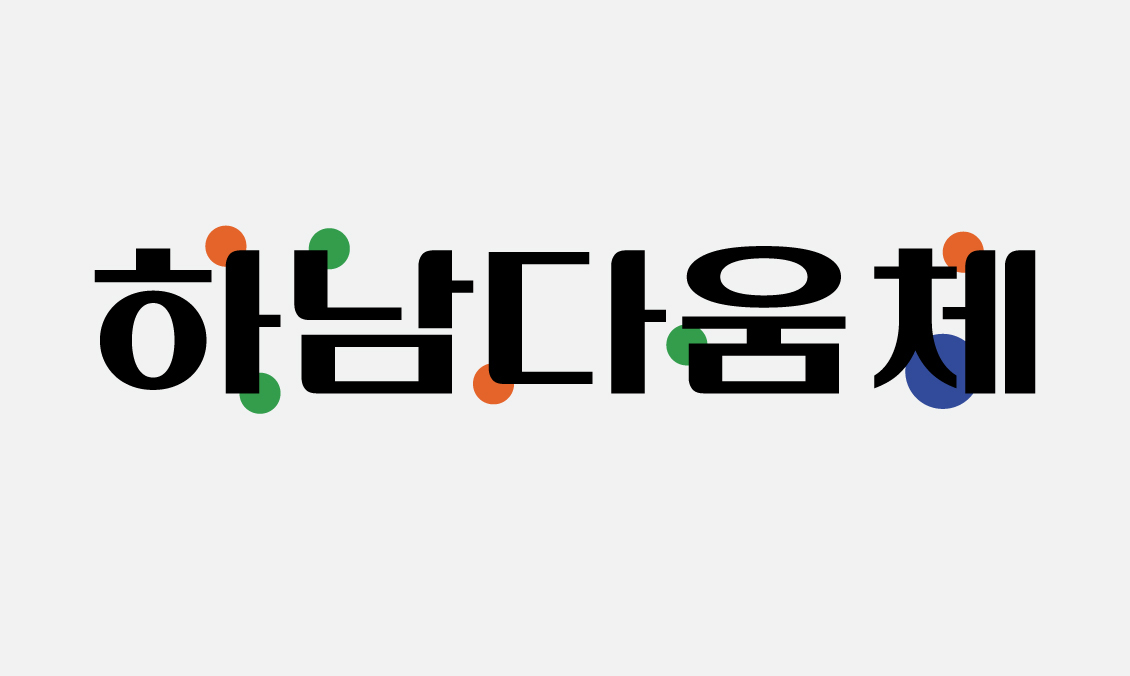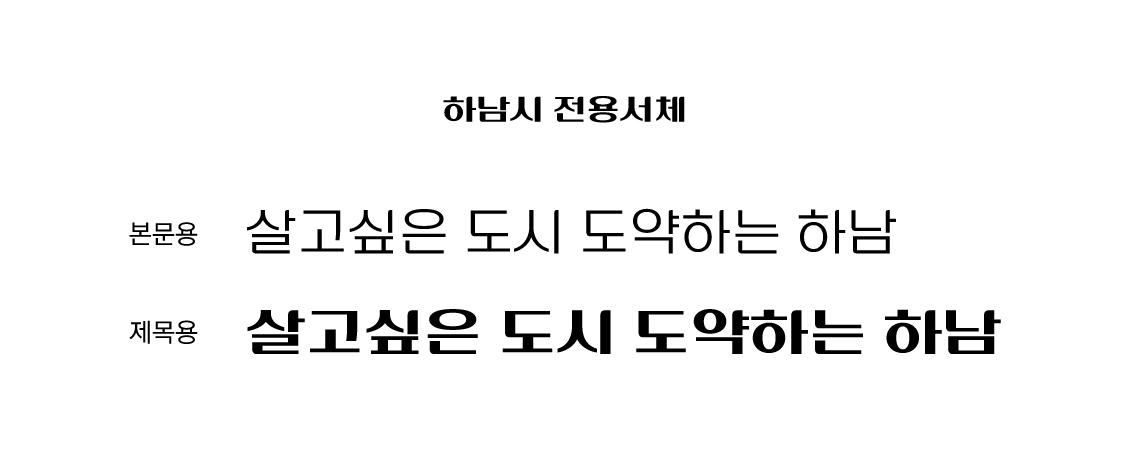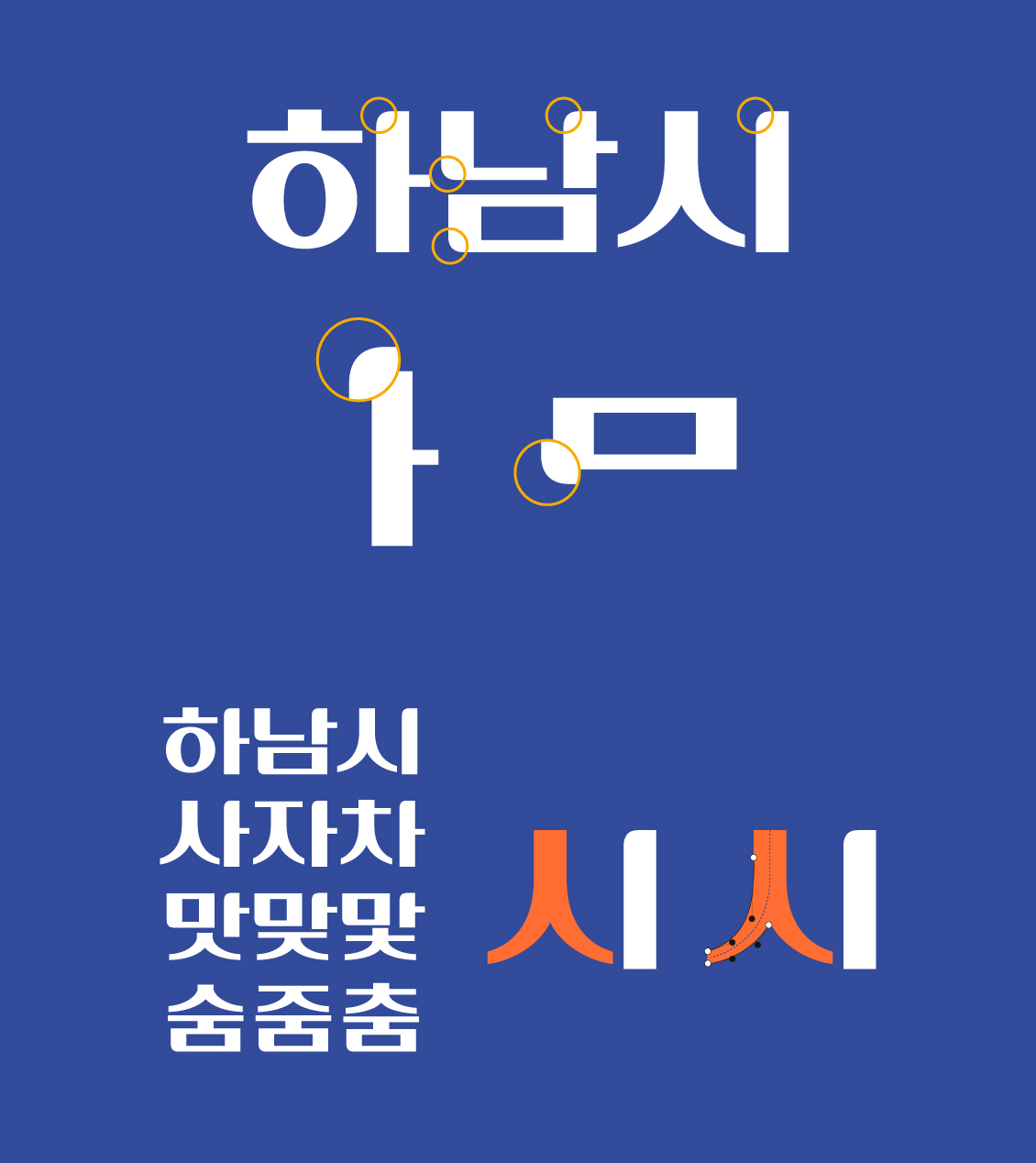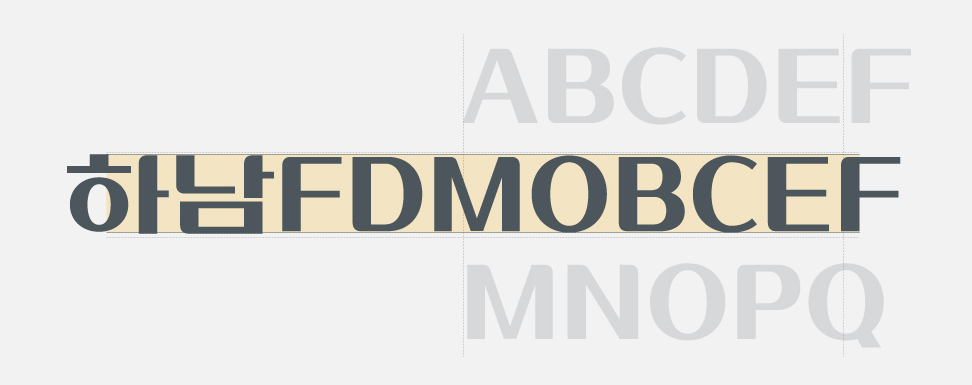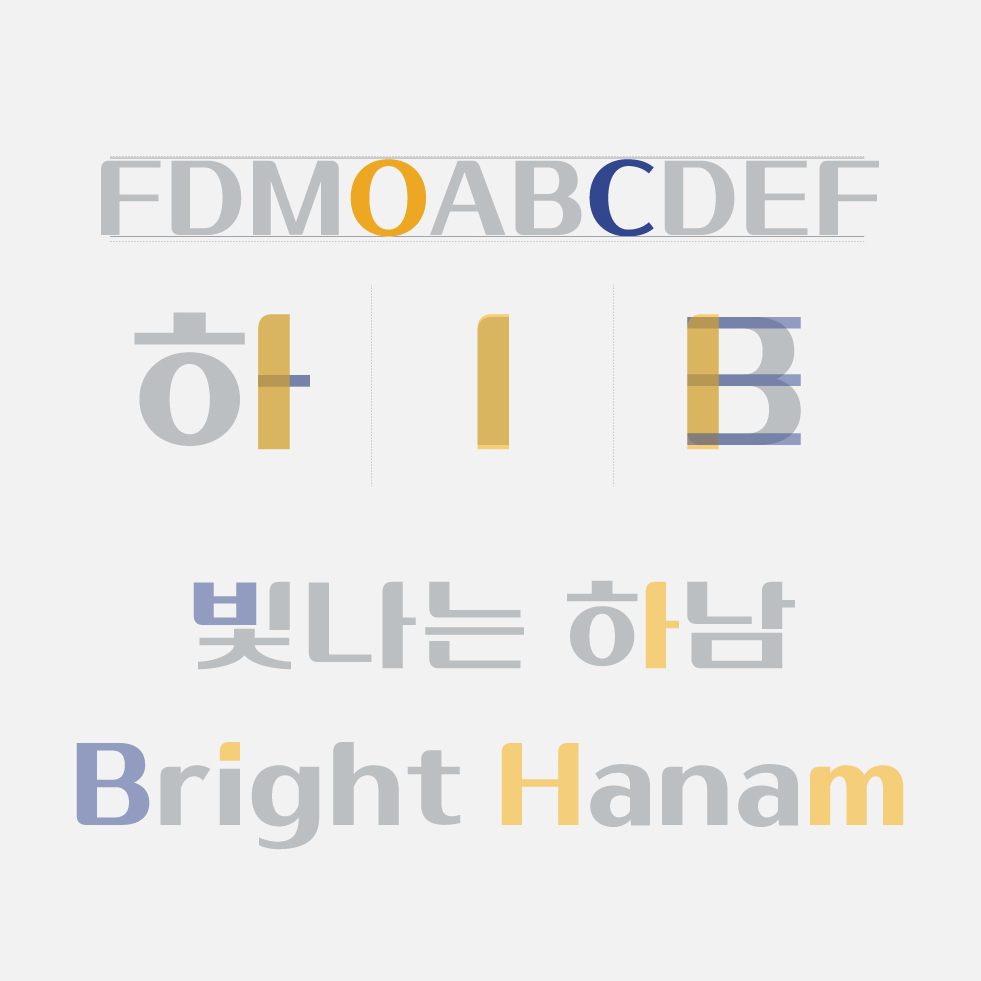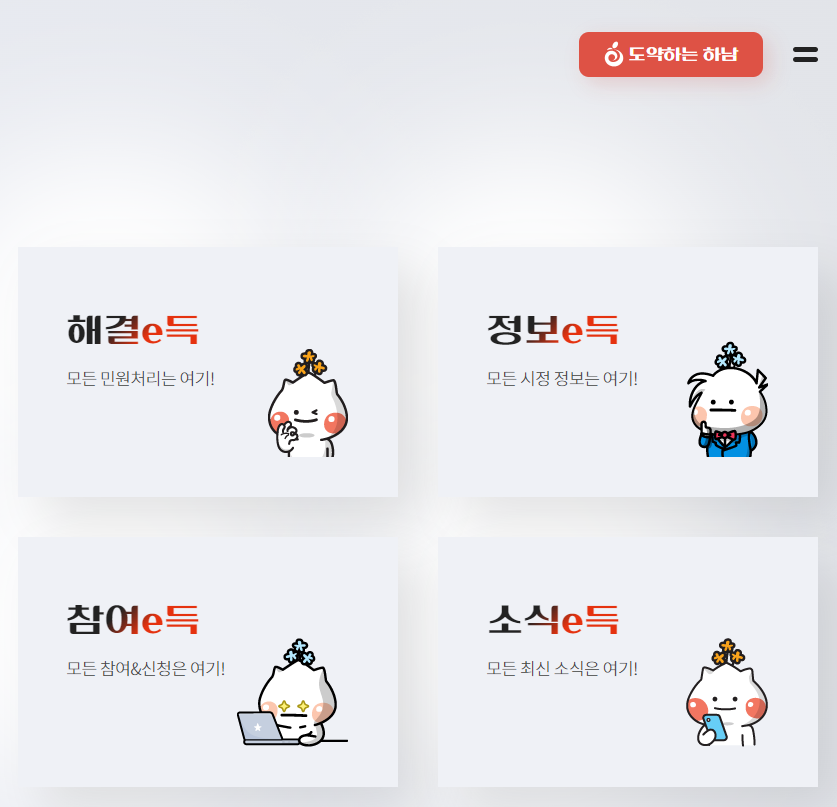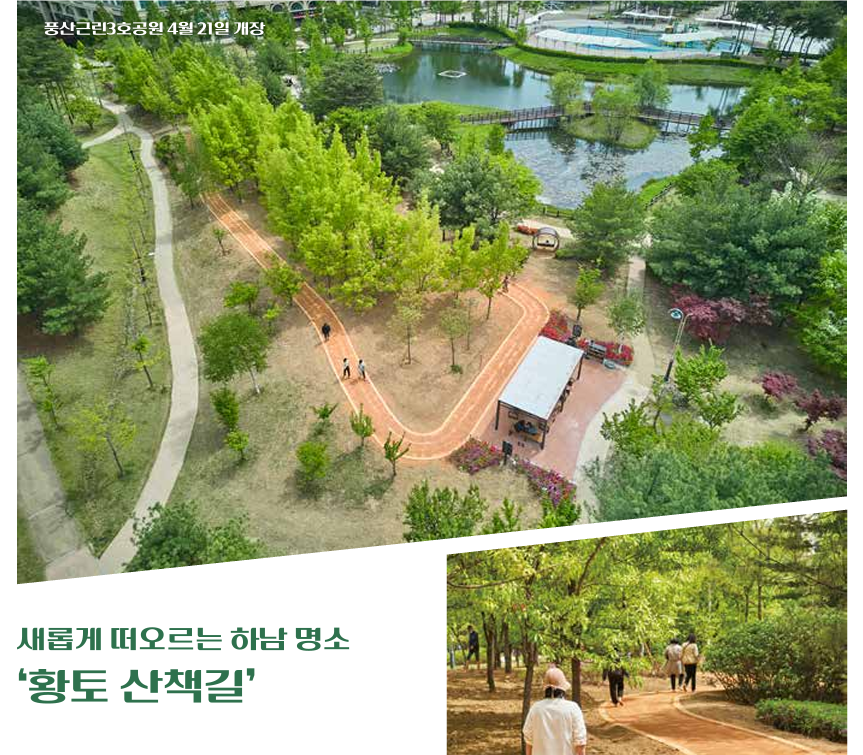
오늘 알아볼 서체는 하남시의 새로운 슬로건 '살고 싶은 도시, 도약하는 하남'에 맞게 하남시 전용서체로 개발한 「하남다움체」입니다. 안정됨 속에 역동하는 하남시의 정체성을 서체로 잘 표현하기 위해 기존 국문 로고타입의 큰 특징들을 반영하여 발전시키는 방식으로 제작되었습니다.
안정적인 하남다움
하남다움체는 타이틀로 쓰기 좋은 제목용, 여러 콘텐츠에 범용적으로 사용 가능한 본문용 두 가지로 개발했습니다. 기본적으로 네모꼴 꽉 찬 구성으로 단단하고 안정감이 느껴집니다.
두꺼운 세로 획의 좌 상단과 일부 꺾임 부분에 기존 로고타입에서 볼 수 있는 굴림 효과를 일정하게 넣어 하남시의 정체성을 유지하면서 안정감 있고 부드러운 인상이 느껴지도록 했습니다. ‘ㅅ’, ‘ㅆ’, ‘ㅈ’, ‘ㅉ’, ‘ㅊ’ 등 ‘ㅅ’계 자소에 여유로운 곡선은 온화하고 풍요로운 느낌을 줍니다.
역동적인 하남다움
제목용 서체에서 볼 수 있는 굵은 세로 획과 얇은 가로 획의 시원한 획대비는 하남시의 역동적인 성장을 표현한 것으로 하남시의 이미지를 더욱 직관적으로 서체화했습니다.
영문에서도 동일한 획대비 특징과 단단하고 강한 인상을 느낄 수 있는데요. 영문 제작에서도 국문과의 혼용을 고려하여 최적의 크기 및 글줄로 보이도록 디자인했으며, 굴림 효과와 여유로운 곡선 등을 적용했습니다.
하남다움체의 활용
'인간다움' 등과 같이 앞에 붙는 단어를 그만의 특징으로 명명하는 것에서 착안하여 ‘하남다움체’라는 이름은 시민을 대상으로 한 공모와 투표로 만들어진 이름이라고 합니다. 시민의 아이디어로 만들어진 서체명과 슬로건이 참 멋지다는 생각이 드는데요. 시를 대표하는 서체 개발에 참여했다는 것이 굉장히 의미가 있었던 전용서체 제작 사례였습니다. 감사합니다.